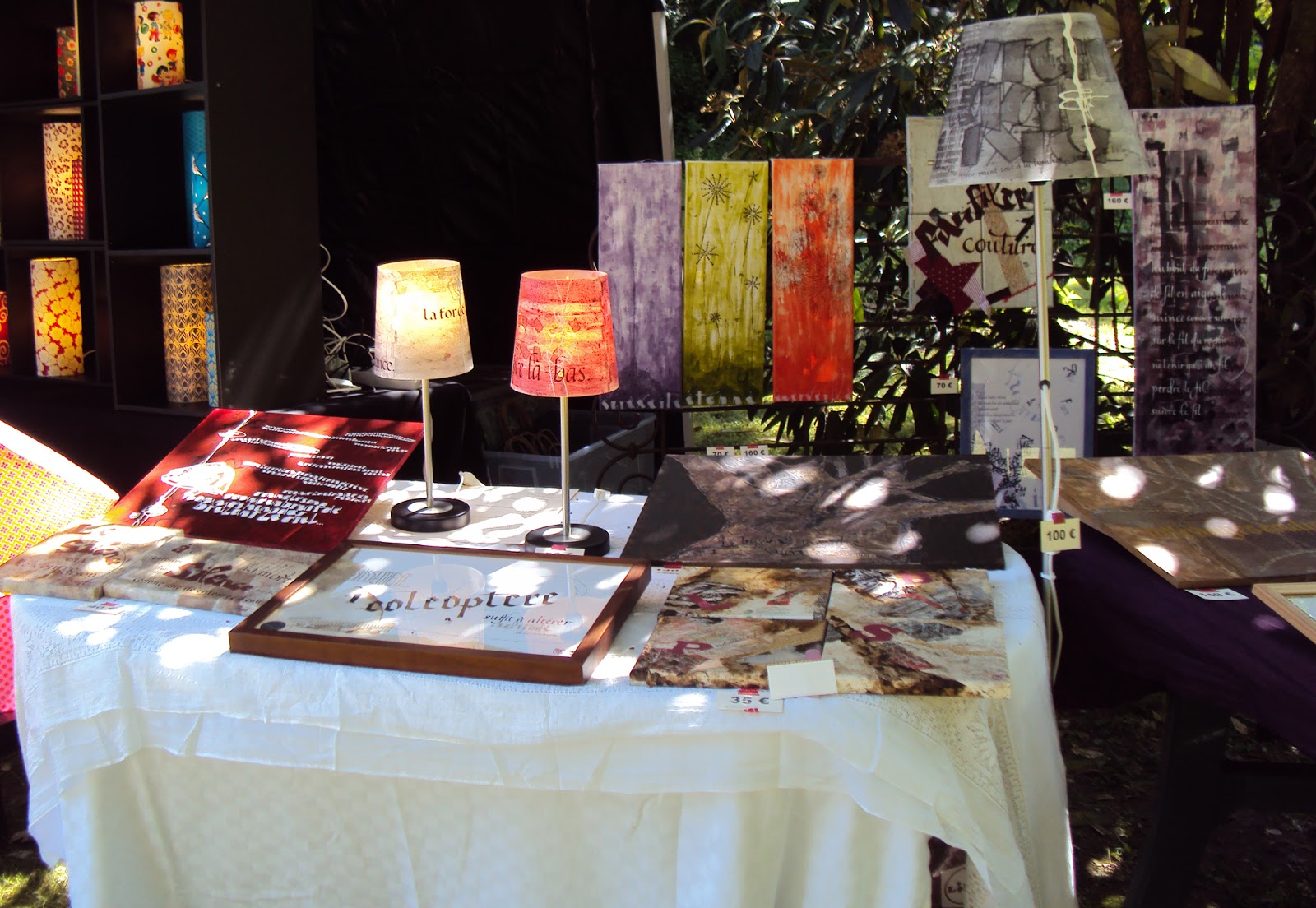
Fin octobre, j'ai été contactée par une ancienne collègue repartie dans son Limousin...
Elle cherchait un cadeau original afin de célébrer la thèse de médecine que devait passer sa sœur le 17 novembre à 17h !
Après quelques réflexions, elle a pensé à de la calligraphie et s'est souvenu de moi...
Je lui ai donc proposé un tableau sur MDF, dimension 55 x 46 cm. Support et dimensions permettant l'envoi par la poste !
Les " consignes " de personnalisation :
- les couleurs : violet, blanc, gris, noir
- le chiffre 17
- le symbole de la médecine : le caducée
- la citation de Franz Kafka : " Le bonheur supprime la vieillesse. "
- une certaine lisibilité
Voici le tableau et quelques détails :
Marché des créateurs à Byans sur Doubs
Dimanche dernier, j'ai participé à mon premier marché de créateurs...
Voici l'affiche :
Cela m'a permis de me rendre compte que ce que je fais plaît ; ça c'est quand même une très bonne chose...
Si l'année prochaine, je refais le déplacement, je prévoirai de petits objets, des cartes ou marque-pages, des petits cadres et bien sûr des lampes ou abats-jours...
Le tout calligraphié évidemment !
Mon stand :
Triple Salto avec Véronique Sabard
Le week-end du 13 et 14 mai, j'ai participé au stage proposé par l'association Apex.
Véronique Sabard (que j'ai eu l'occasion de rencontrer l'année dernière lors d'un autre stage Apex) nous a invité à travailler avec 3 outils scripteurs : le folding pen (ou tire-ligne belge), le ruling pen et le feutre pinceau. Chaque outil produit une trace différente mais induit également un geste différent !
Nous avons effectué bon nombre d'exercices (25 en tout!! une quantité astronomique de papier brouillon a été nécessaire...) pour nous délier les doigts, la main, le poignet, le bras et l'épaule... afin d'appréhender la calligraphie gestuelle qui traduit, selon elle, une manière de tracer la lettre plus qu'une forme de lettre en particulier ! Et pour cela, il faut trouver un certain lâcher prise !!
La base des lettres qu'elle nous a proposée est la typographie de Karl Georg Hoefer : le Salto ou le Saltino datant de 1952.
Voici ce que j'ai réalisé...
| tout petit extrait des exercices (ruling pen) |
| tout petit extrait des exercices (folding pen) |
| ruling pen |
| folding pen |
| ruling pen |
| folding pen |
| feutre pinceau |
| versions de Véronique |
Stage avec Arlette à Oberbronn
Ce week end, je suis allée, avec 4 de mes callicop's, à Oberbronn pour participer à un stage de calligraphie que je pourrais intituler " Traces, voyages/paysages et couleurs " organisé par Liliane Buchi mais animé par une autre callicop's : Arlette !
Connaissant assez bien Arlette, nous savions que le stage allait être dense et créatif... nous n'avons pas été déçues !!
J'y suis allée cet après-midi...
Environ 70 œuvres permettent de se rendre compte de l'étendue des possibles en calligraphie latine ("classique" ou contemporaine).
Sur papier ou sur bois, faits avec différents médiums, à partir de diverses écritures et évidemment selon différents styles (plus d'une vingtaine d'exposants)...
Une chouette expo et un bon moment de partage !
Voici quelques-uns des différents panneaux, objets et quelques détails d’œuvres :